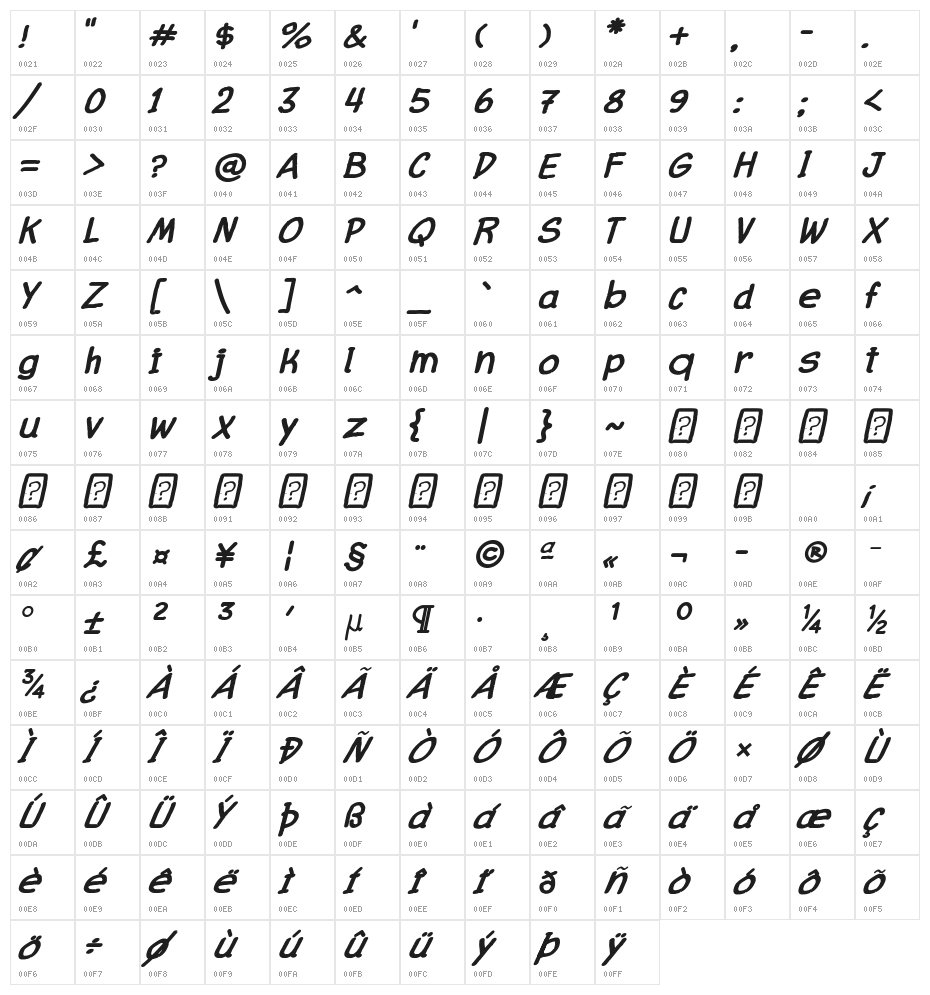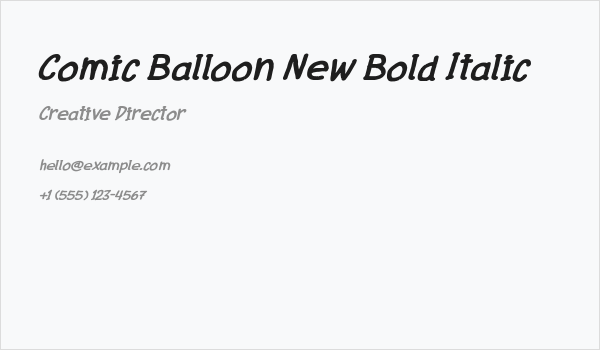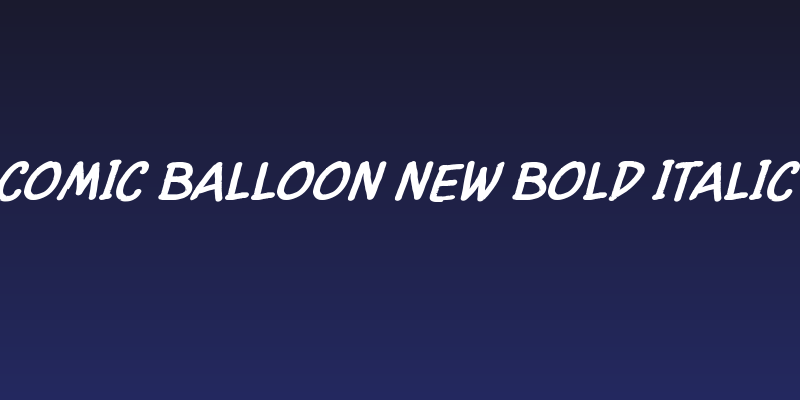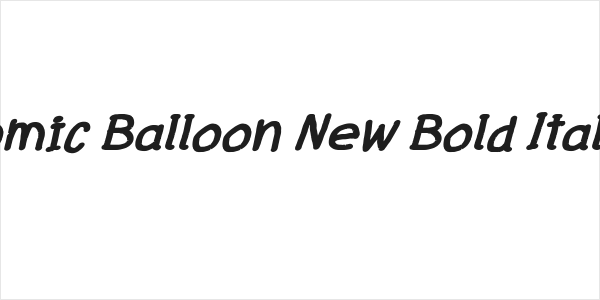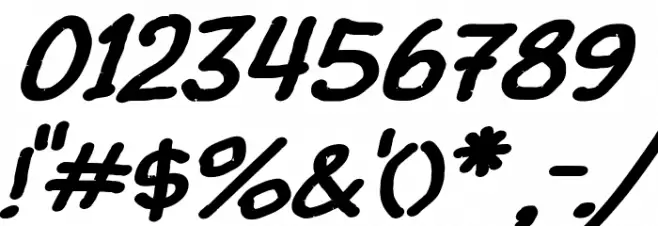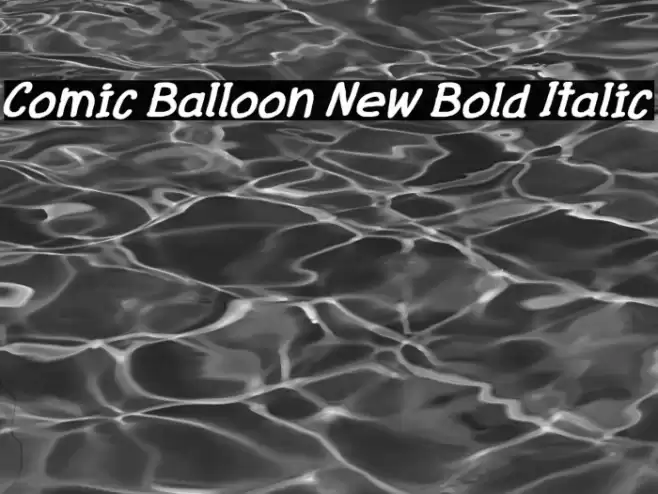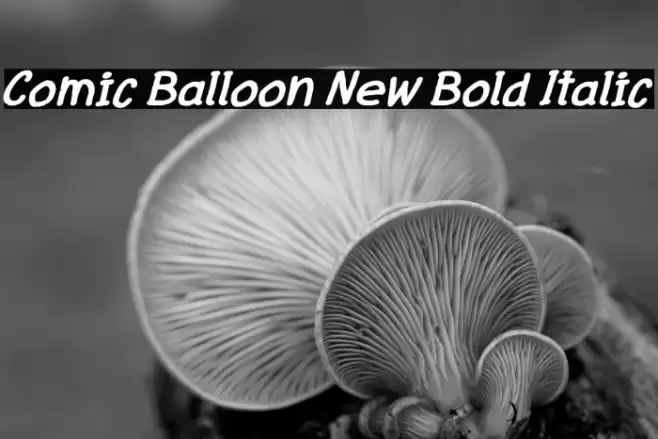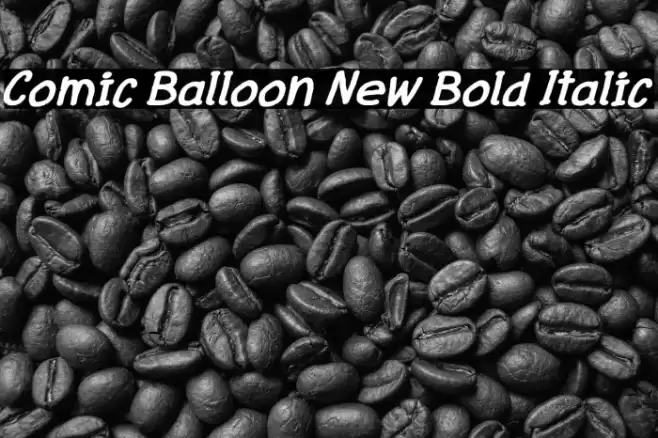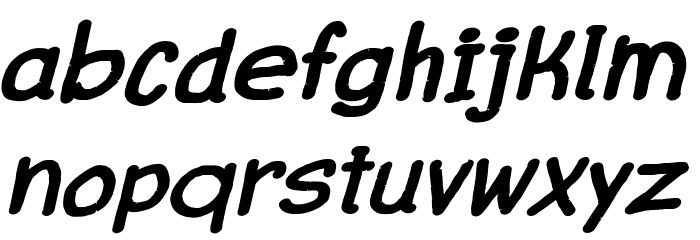
Comic Balloon New Bold Italic Font
| Nom | Comic Balloon New Bold Italic |
| Famille de police | Comic Balloon New |
| Style | ComicBalloonNew-BoldItalic |
| Poids | Bold Italic |
| Style général | Playful, Comic |
| Projets proposés | Ideal for comic books, children's books, playful branding, and informal posters. |
| Auteur | Fonts by Galdino Otten Fonts |